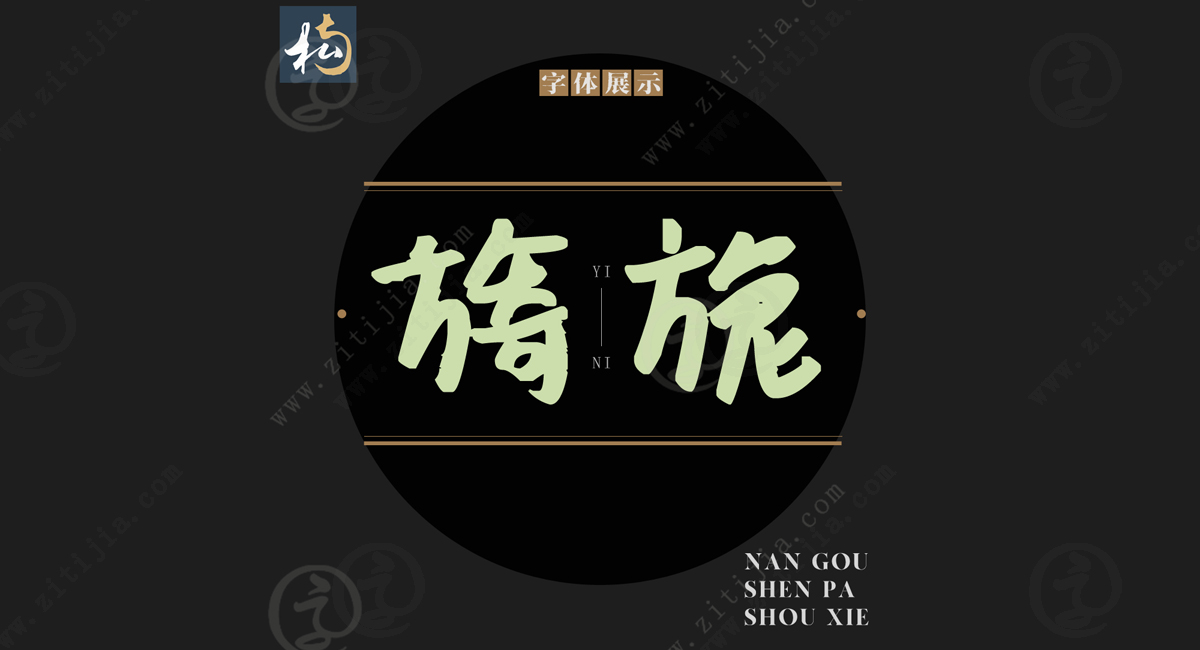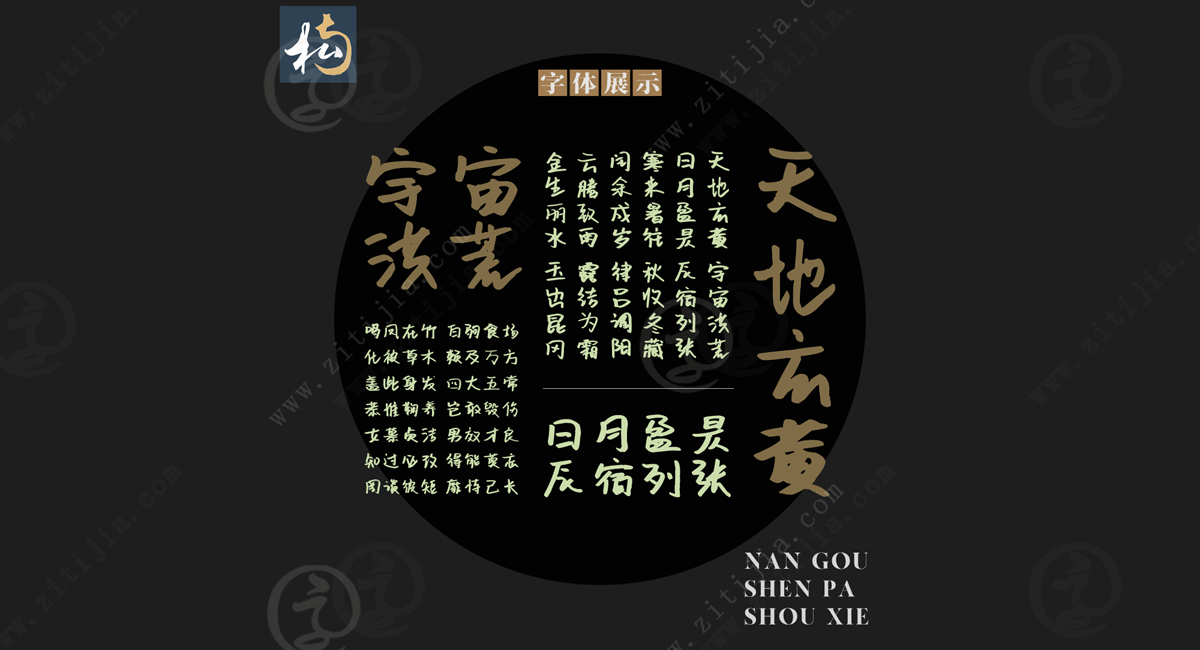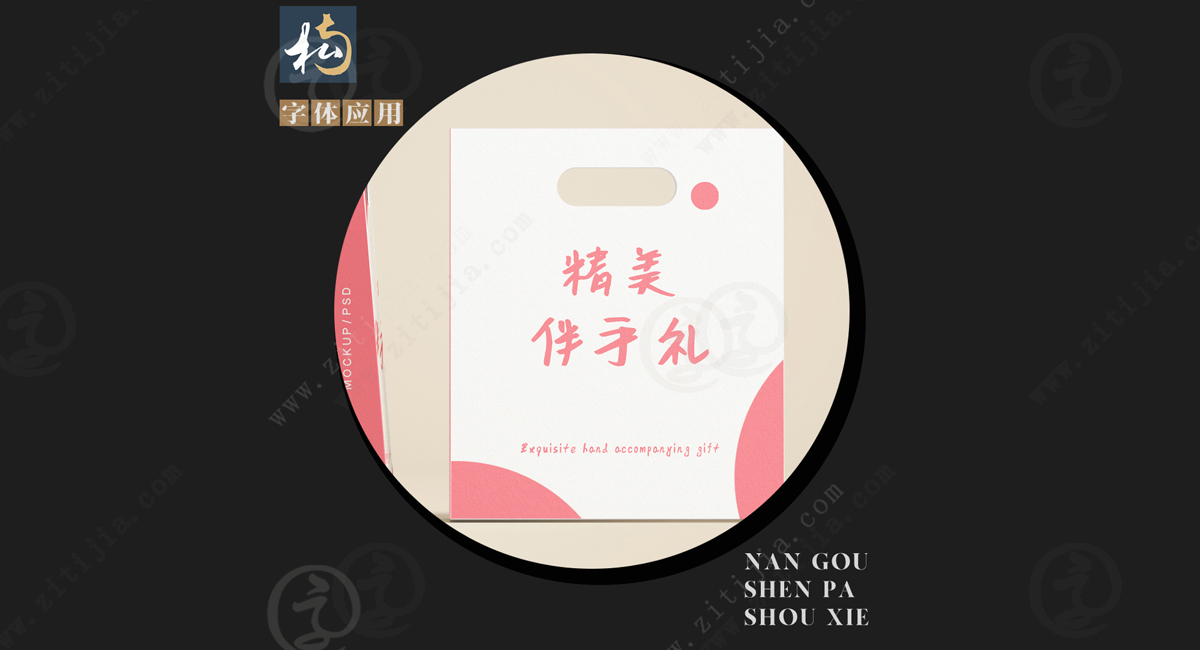
笔画粗犷而又自然随性,字体家网站南构审帕手写字体欣赏
南构审帕手写字体是一种独特的艺术字体,它的笔画粗犷而又自然随性,给人一种放松、随意的感觉。这种字体不仅适合于各种场合的设计,而且也非常适合那些喜爱书法和绘画的人。
美学价值
作为一种艺术字体,南构审帕手写字体具有极高的美学价值。它的线条粗犷有力,内含着一种原始的美感。每一笔都充满了生命的力量,表达出了一种随性、自由、奔放的感觉。这种字体的设计灵感来自人们日常生活中自然、随意的书写方式。因此,这种字体与生活息息相关,更容易引起人们的共鸣。
实用价值
同时,南构审帕手写字体也具有极高的实用价值。它非常适合用于各种场合的设计,无论是书籍装帧、平面设计、广告设计还是字体设计等等,它都能够体现出极高的艺术价值和实用价值。这种字体既可以用于温馨、贴近人民的设计,也可以用于独特、前卫的设计,无论用在哪个领域,都能够让人眼前一亮。
总之,南构审帕手写字体在艺术性和实用性方面都具有极高的价值。它的设计风格独特,线条粗犷而有力,内含着一种原始的美感,能够引起人们的共鸣。如果您是一位热爱设计的人,喜欢创新、追求自由与个性,那么南构审帕手写字体一定是您不可或缺的选择。
南构审帕手写